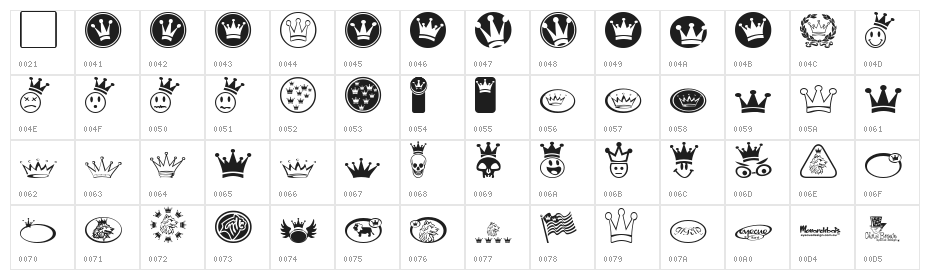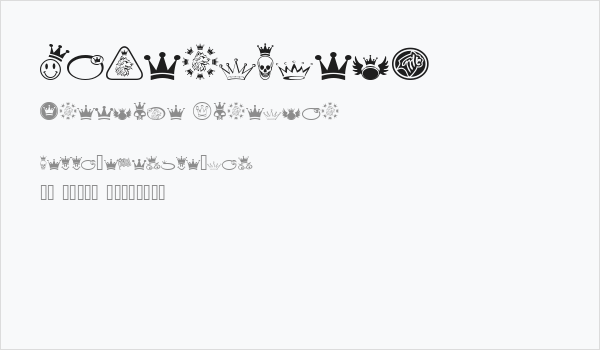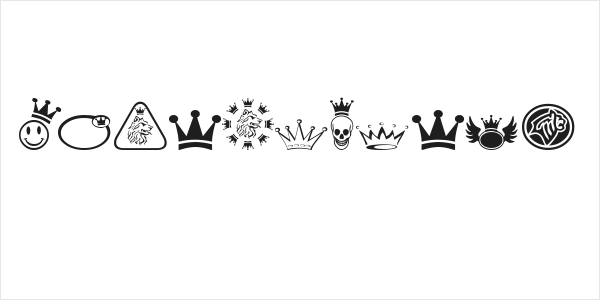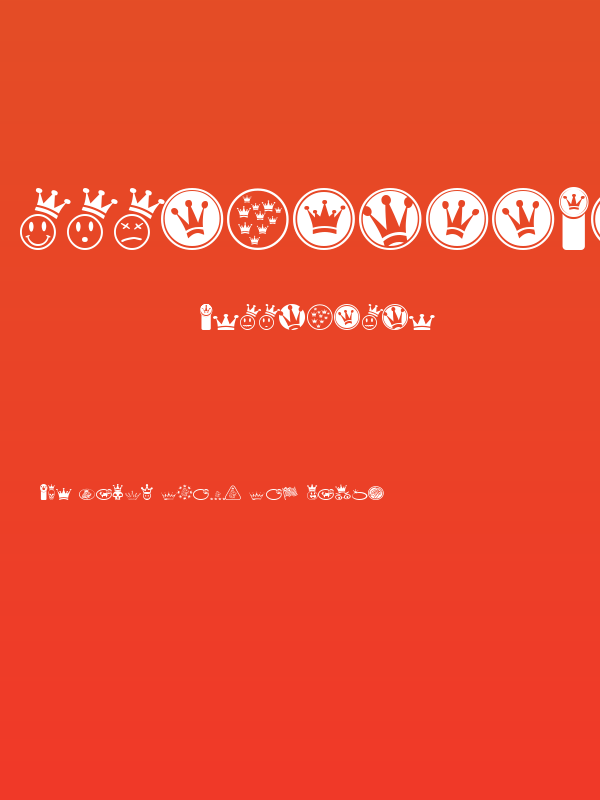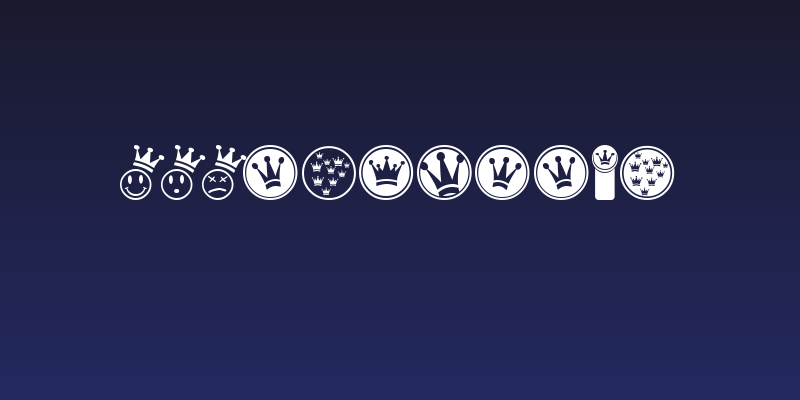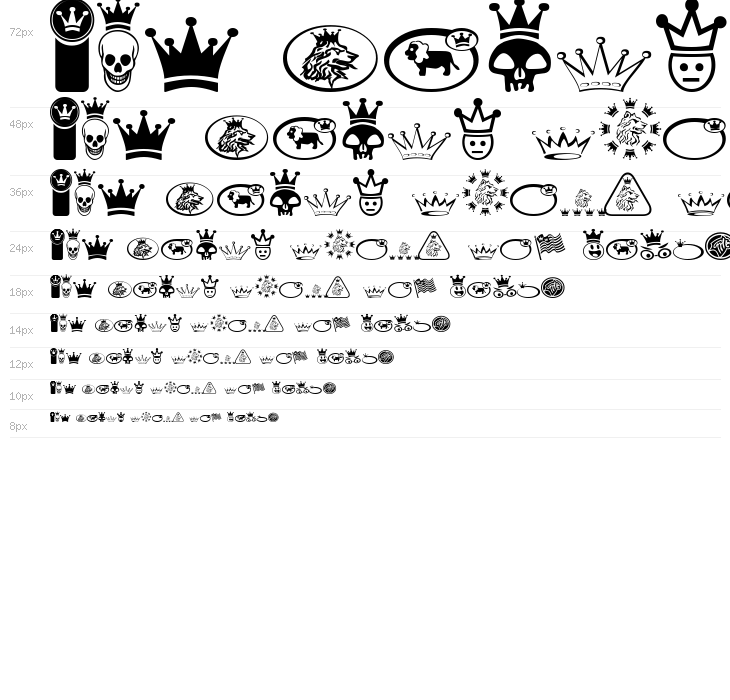
Monarchbats Font
Fonts by Eyecue Design - Chris Brown
| Anwendungsfall | Logos, Decorative elements |
| Vorgeschlagene Projekte | Ideal for use in graphic design projects, such as creating logos, emblems, or decorative borders. Suitable for party invitations, themed events, or any project requiring a regal yet fun aesthetic. |